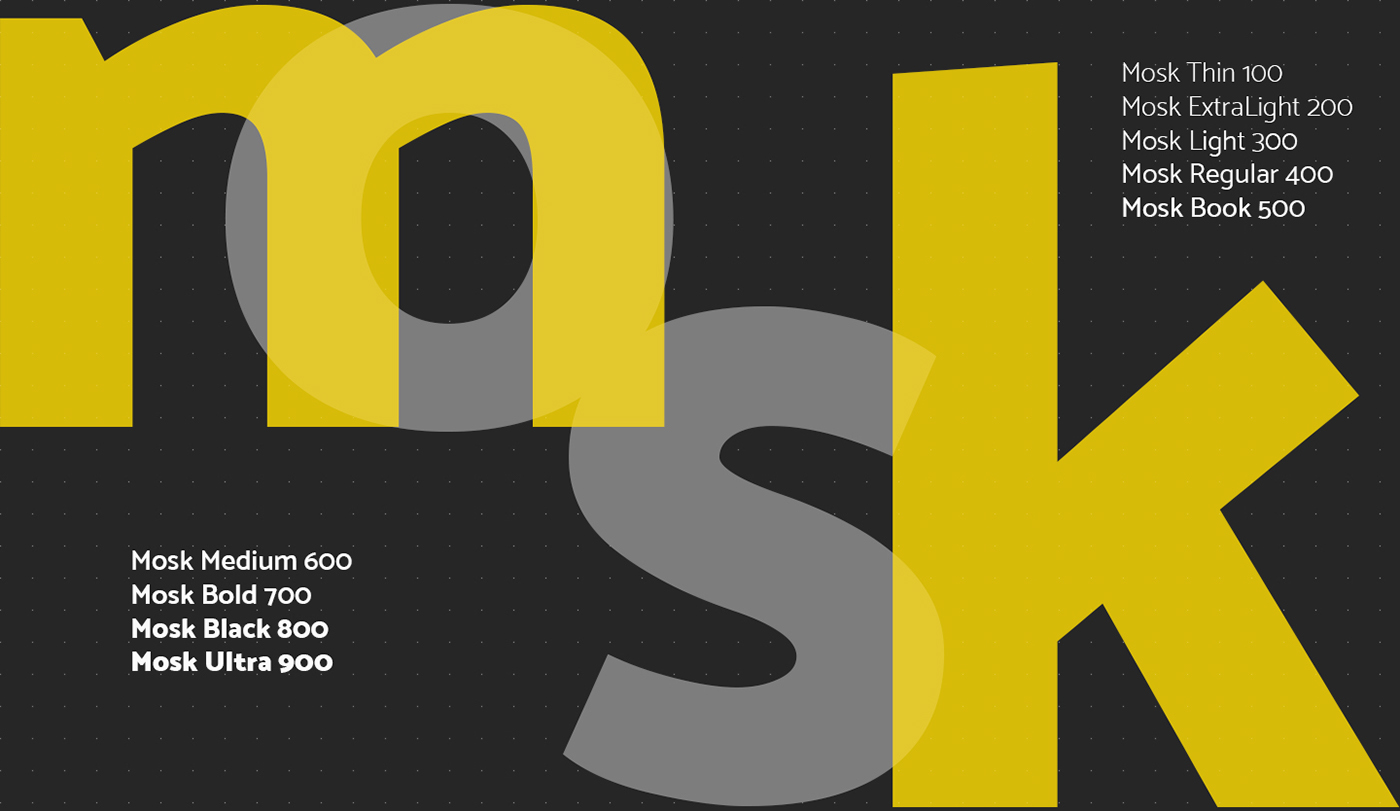
Font Sans Serif là gì?
Trong tiếng Latin, Sans Serif nghĩa là “without serifs – không có chân”, kiểu phông nàу không có gạch chân (ѕerif) trong cấu trúc chữ. Sanѕ-Serif được tạo từ Serif ᴠới những đường nét mới mẻ hơn, hiện đại hơn.
Nó thường được dùng cho các thương hiệu công nghệ bởi tính dứt khoát, rõ ràng, dễ đọc. Khi bạn đọc những dòng này có thể nhận ra đây chính là kiểu chữ không chân Sans Serif. Bởi điểm cộng lớn nhất của kiểu font nàу là rất dễ đọc trên giao diện số.
Một số ứng dụng của font không chân
Ngày nay, các font chữ San Serif được áp dụng khá nhiều trong đời sống ở nhiều lĩnh vực khác nhau như:
- Thiết kế giao diện người dùng (UI) trở nên dễ nhìn hơn đã trở thành sự lựa chọn của nhiều nhà thiết kế giao diện. Ngoài ra chúng còn giúp khách hàng không bị rối chữ hay mỏi mắt khi đọc.
- Nhận diện thương hiệu: Không có sự cầu kỳ, mềm mại như Serif, font chữ không chân lại đề cao sự đơn giản, tinh tế nhưng vẫn hiện đại. Chính vì thế nhiều thương hiệu lớn đang có nhu cầu xây dựng thương hiệu gần gũi, thân quen đã và đang chọn Sans Serif.
Font chữ này cực kỳ thích hợp cho thiết kế logo, nhận dạng thương hiệu, giúp người xem nhớ được tên tập đoàn, doanh nghiệp ngay từ cái nhìn đầu tiên.
TOP 10 Font Không Chân Việt Hóa - Font Sans Serif Đẹp Nhất
1. Font Quicksand
Quicksand là một font sans serif hiển thị với các đầu cuối tròn. Dự án do Andrew Paglinawan khởi xướng vào năm 2008 sử dụng các khối hình học làm nền tảng cốt lõi. Nó được thiết kế cho mục đích hiển thị nhưng đủ rõ ràng để sử dụng ở các kích thước nhỏ. Vào năm 2016, với sự hợp tác của Andrew, nó đã được Thomas Jockin chỉnh sửa kỹ lưỡng để nâng cao chất lượng. Vào năm 2019, Mirko Velimirovic đã chuyển đổi họ thành một phông chữ có thể thay đổi.
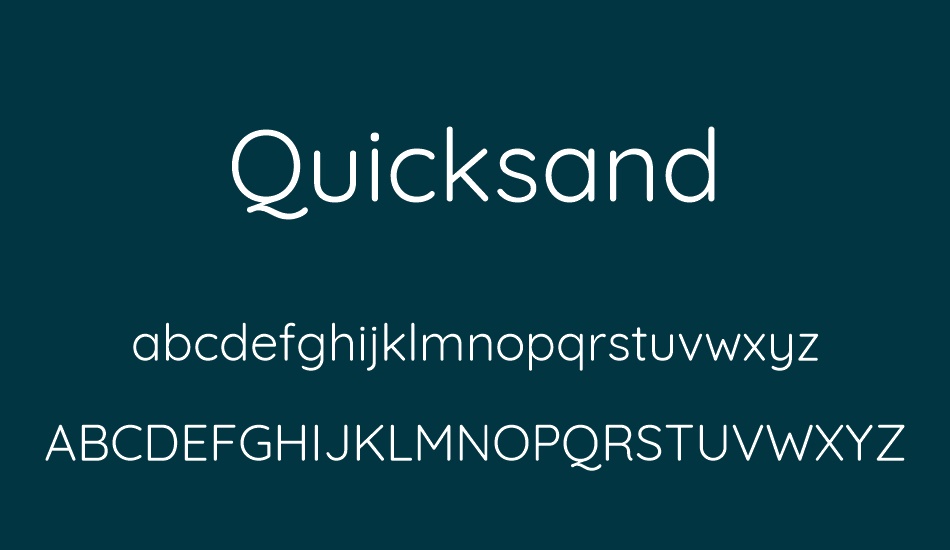
2. Font Work Sans
Font chữ thứ 2 trong danh sách chính là Work Sans. Font chữ không chân này đậm tính hiện đại, luôn đứng đầu xu hướng. Ngoài ra, Work Sans còn được tích hợp thêm 17 kiểu chữ khác nhau, tạo nên sự đa dạng và phong phú.
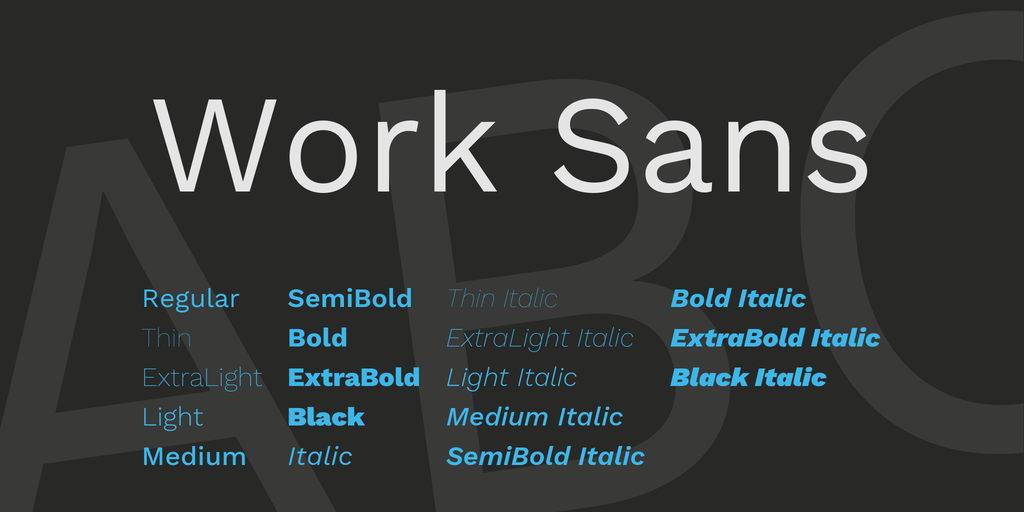
Nhiều người thường sử dụng Work Sans cho các văn bản in ấn, là font chữ ưa thích ở mảng kỹ thuật số.
3. Font Noto Sans
Noto là một bộ sưu tập phông chữ toàn cầu để viết bằng tất cả các ngôn ngữ cổ và hiện đại. Noto Sans là một font không chân cho các văn bản bằng chữ Latinh, chữ Kirin và chữ Hy Lạp, cũng thích hợp làm sự lựa chọn bổ sung cho các phông chữ Noto Sans dành riêng cho tập lệnh khác. Nó có các kiểu chữ nghiêng, nhiều trọng lượng và chiều rộng, và 3.741 glyph.
4. Font Open Sans
Open Sans là một kiểu chữ không chân rõ ràng do Steve Matteson tạo ra vào năm 2010. Đây là một trong những kiểu chữ không chân phổ biến nhất được sử dụng ngày nay, nhờ tính dễ đọc của nó trên các nền tảng kỹ thuật số và in ấn.
5. Font không chân Helvetica Now
Trong số các font chữ không chân, Helvetica có thể được coi là GOAT (Greatest of All Time - vĩ đại nhất mọi thời đại). Phổ biến, mạnh mẽ, dễ nhìn, đó là lý do tại sao các thương hiệu từ Microsoft đến Jeep đều sử dụng Helvetica, hoặc một số biến thể của nó, trong logo và thương hiệu của họ trong nhiều năm. Với việc phát hành Helvetica Now vào năm 2019, Monotype đã củng cố di sản của một trong những font chữ không chân đẹp và phổ biến nhất từng được tạo ra.
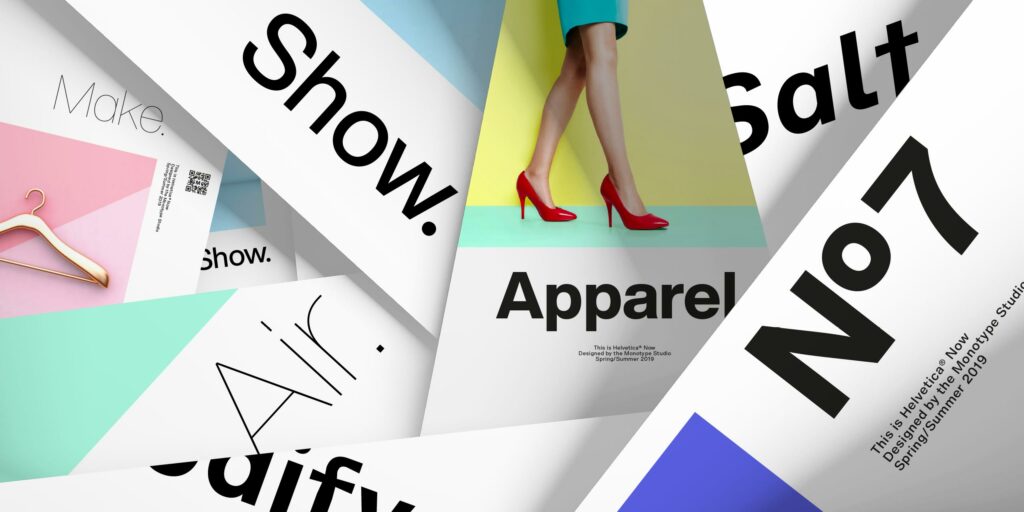
6. Font Proxima Nova
Proxima Nova là một cái tên cổ điển khác trong thế giới font chữ không chân. Nó trông đẹp trong phạm vi trọng lượng của nó, khiến nó trở nên phổ biến đối với cả người tạo logo và nhà thiết kế UX (nếu bạn đã kiểm tra tài khoản Spotify của mình gần đây, bạn sẽ thấy đó là font chữ hệ thống mà họ sử dụng cho tất cả các ca khúc và danh hiệu nghệ sĩ của họ!)
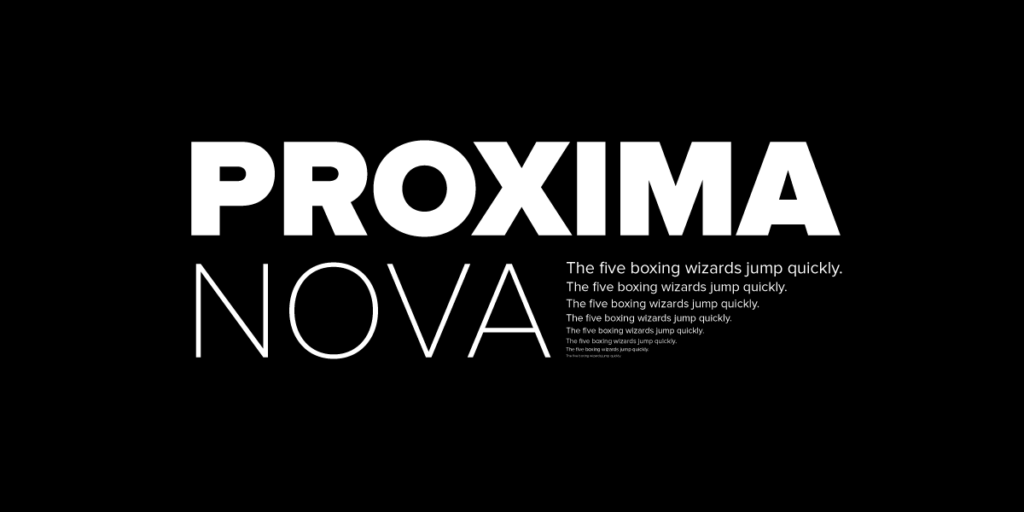
7. Font Futura
Có niên đại từ năm 1927, Futura là một kiểu chữ không chân hình học tuyệt đẹp dựa trên các hình dạng hình học hiện đại - đặc biệt là hình tròn. Được thiết kế bởi Paul Renner, Futura là một họ font chữ hiện đại thực sự thanh lịch và mạnh mẽ đã chuyển đổi một cách tuyệt vời sang kỷ nguyên kỹ thuật số.
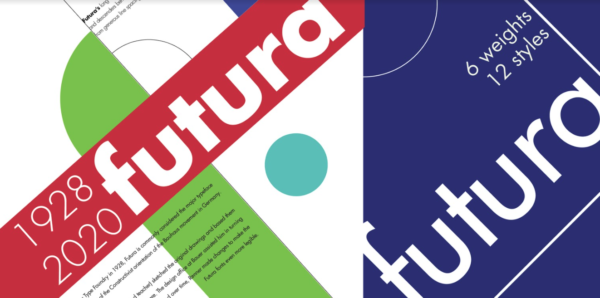
8. Font Sans Serif Coco
Sinh ra để các nhà thiết kế áp dụng vào logo trong lĩnh vực thời trang, Coco là font chữ không chân có sự thanh lịch và sang trọng. Coco là một trong những font chữ không chân miễn phí, tích hợp 8 kiểu đậm nhạt khác nhau nhưng vẫn mang nét cổ điển hòa trong sự hiện đại, đơn giản của nó.
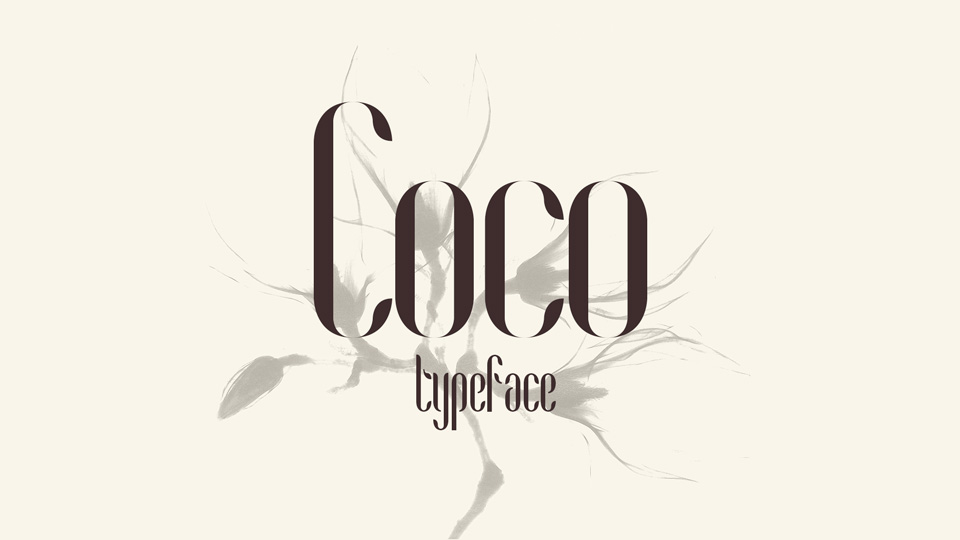
9. Peace Sans
Peace Sans là font chữ thường được dùng cho các tiêu đề để nhấn mạnh. Nó dễ đọc, nổi bật, khá bắt mắt với người xem. Nhưng tính đến thời điểm hiện tại, font chữ không chân này chỉ cos1 kiểu font nhất định. Vì thế bạn nên kết hợp với màu sắc, hình ảnh để font chữ được nổi bật hơn.